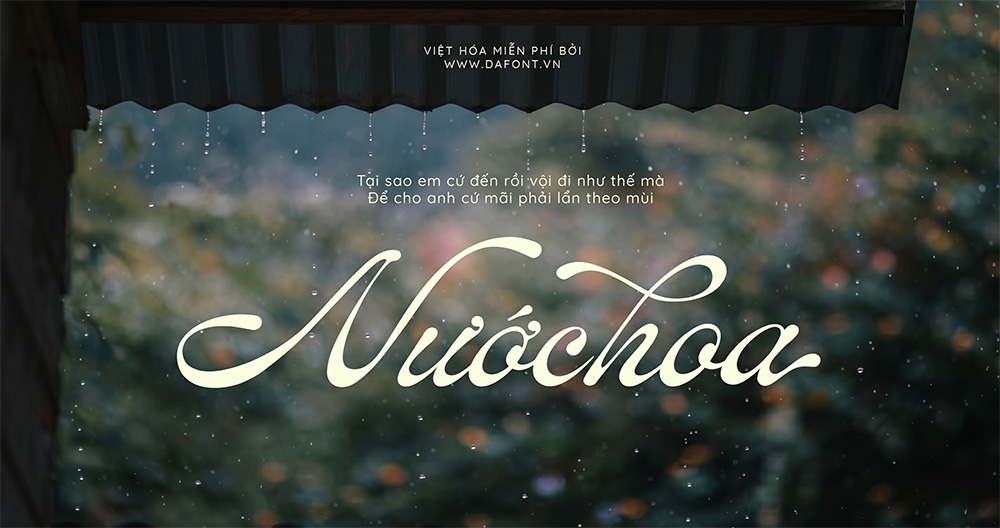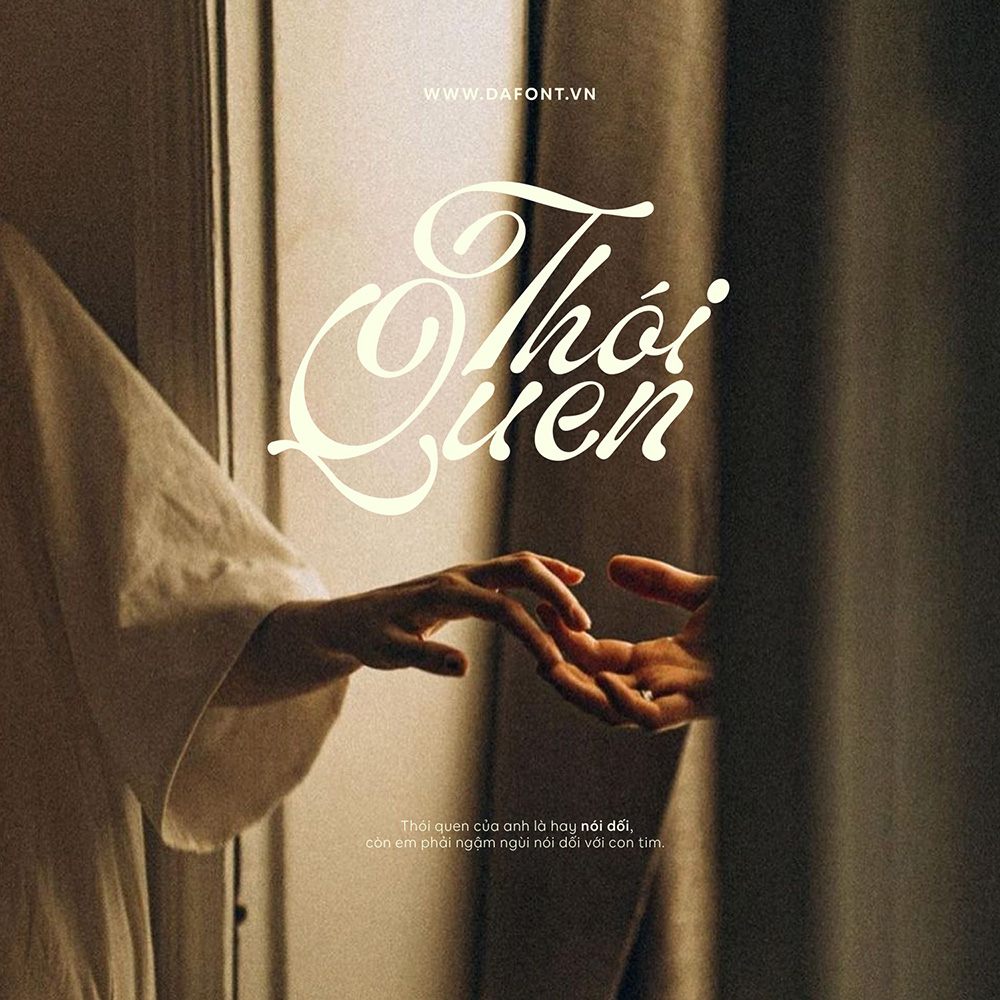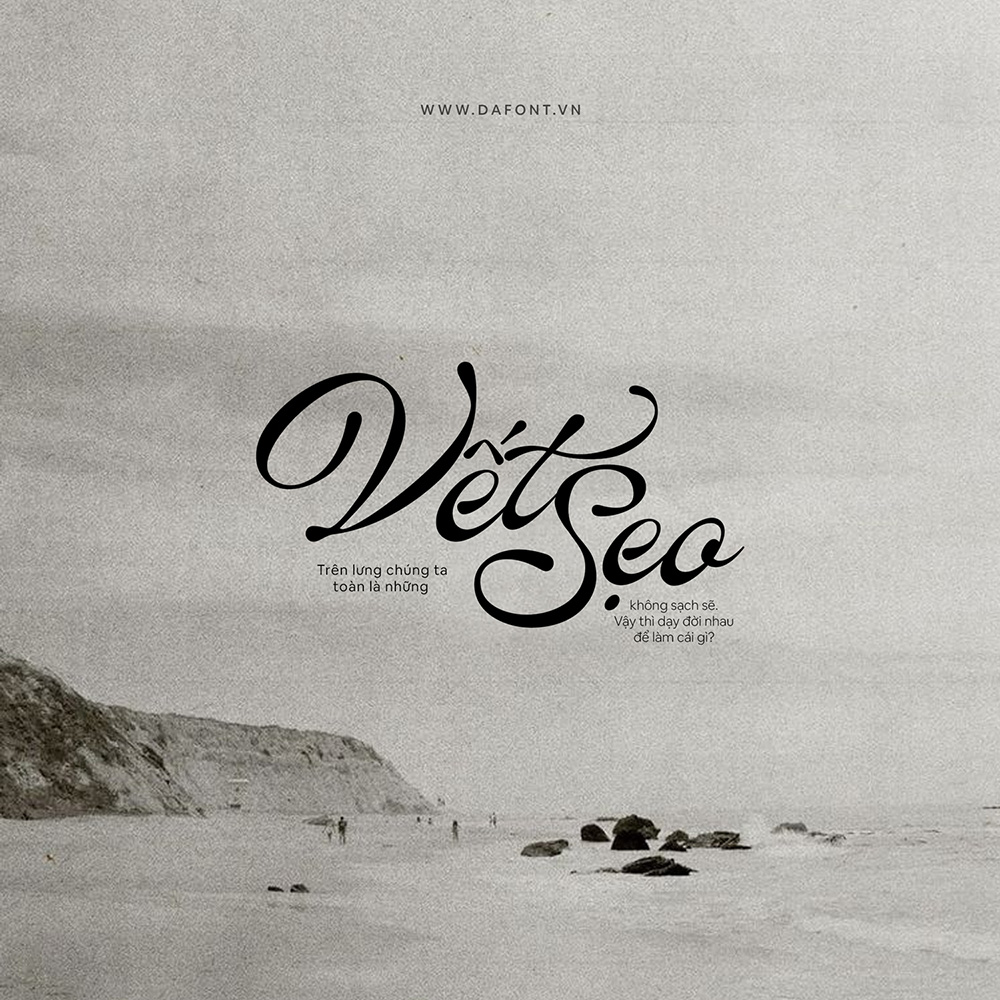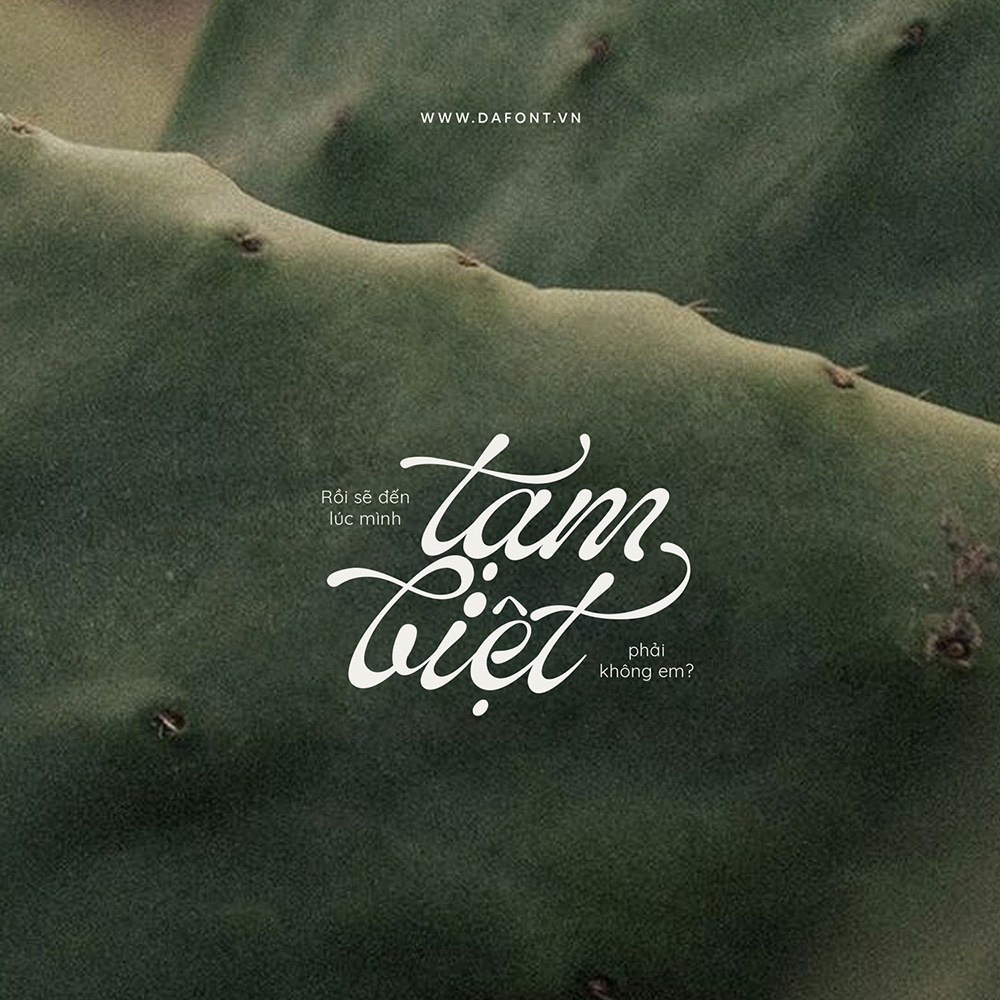
Font Việt Hóa - ED Lavonia Mang Phong Cách Cổ Điển Và Tinh Tế
ED Lavonia là một font chữ viết tay được thiết kế bởi Emyself Design, nổi bật với phong cách cổ điển và sự tinh tế trong từng nét chữ. Đây là một kiểu chữ mang lại cảm giác sang trọng và thanh lịch, phù hợp cho nhiều dự án thiết kế khác nhau.
Font chữ này có hơn 90 Stylistic sets, Contextual Alternative và Ligatures vì vậy nó giúp tăng thêm tính thẩm mỹ khiến các tác phẩm của bạn trở nên thú vị hơn. Một số ký tự thay thế cũng được việt hóa đầy đủ do đó bạn có thể dễ dàng kết hợp các chữ cái để tạo ra nhiều thiết kế ấn tượng hơn.
ED Lavonia là một font chữ serif mang phong cách sang trọng, hiện đại, thường được sử dụng trong các thiết kế cao cấp như branding, tạp chí, poster và social media.